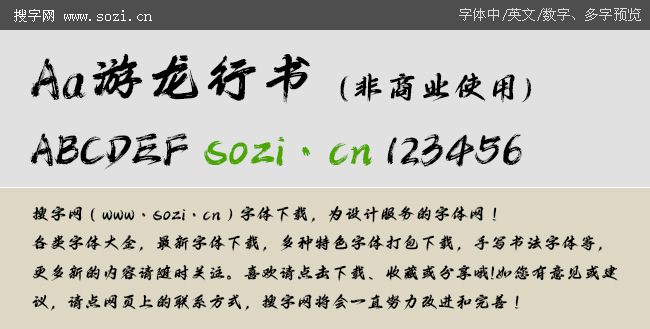
Aa游龍行書
搜字網(wǎng)給大家提供一款A(yù)a游龍行書(非商業(yè)使用)中文字體下載,Aa游龍行書是一款手寫風(fēng)格的書法字體,該字體筆畫自然隨性,書寫簡單大氣,字體結(jié)構(gòu)肆意灑脫,視覺效果非常棒。適合應(yīng)用于海報(bào)設(shè)計(jì)、包裝設(shè)計(jì)、網(wǎng)頁設(shè)計(jì)等應(yīng)用(此字體為個(gè)人非商用版,商用可以聯(lián)系QQ:1006760504)。